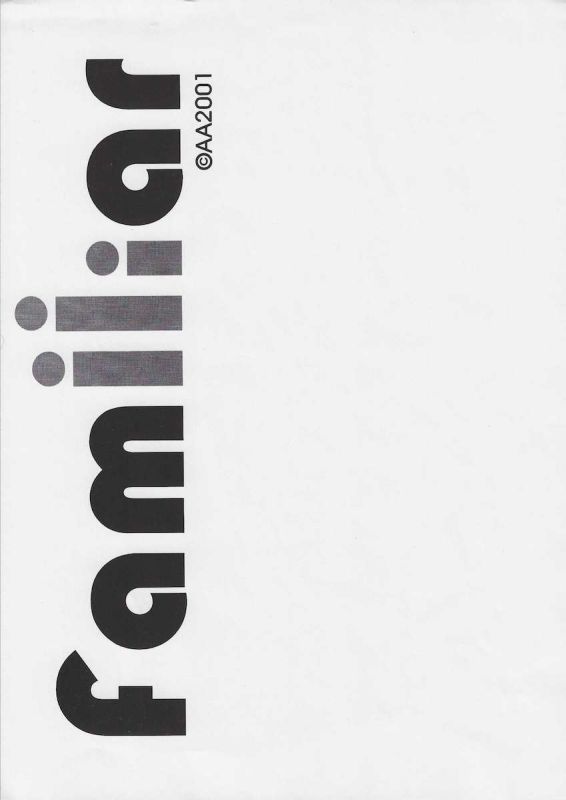
Familiar é uma impressão gráfica de Avelino de Araújo realizada em 2001, vinculada à poesia visual, à poesia experimental, à arte conceitual, à tipografia e às investigações intersígnicas relacionadas ao campo do Poema Processo.
Avelino de Araújo
Data: 2001
Dimensões: 29,5 x 21,1 cm
Familiar é uma impressão gráfica de Avelino de Araújo realizada em 2001, vinculada à poesia visual, à poesia experimental, à arte conceitual, à tipografia e às investigações intersígnicas relacionadas ao campo do Poema Processo. A composição utiliza a palavra familiar como estrutura central e transforma seus caracteres em elementos visuais autônomos. As letras aparecem em grandes dimensões, organizadas verticalmente na folha e impressas predominantemente em preto, enquanto as três letras i são apresentadas em tons de cinza. Os pontos e as hastes dessas letras possuem tamanhos diferentes, criando uma sequência semelhante a figuras humanas reunidas. Essa configuração permite interpretar os três caracteres como integrantes de uma família, possivelmente adultos e criança, estabelecendo uma relação direta entre a forma tipográfica e o significado da palavra. Avelino de Araújo converte a escrita em imagem e utiliza diferenças de escala, posição e tonalidade para construir uma representação sintética das relações familiares. As letras deixam de funcionar apenas como componentes linguísticos e passam a atuar como corpos, presenças e personagens. A palavra familiar também apresenta diferentes sentidos em português, podendo indicar aquilo que pertence à família, aquilo que é conhecido ou habitual e uma pessoa ligada por parentesco. A obra explora essa ambiguidade e aproxima reconhecimento verbal, identidade, convivência, semelhança e diferença. As três letras i destacadas sugerem indivíduos que compartilham a mesma estrutura básica, mas possuem proporções distintas, indicando diversidade dentro de uma unidade coletiva. O espaço vazio ao redor da palavra amplia sua presença e reforça a economia visual da composição. A orientação vertical exige que o observador modifique a posição habitual de leitura, transformando o ato de reconhecer a palavra em experiência corporal e perceptiva. Familiar integra a produção de Avelino de Araújo baseada na apropriação de letras, palavras e códigos tipográficos como matéria de construção poética e reflexão sobre relações humanas. Na proximidade da última letra aparecem a marca de autoria A A e o ano 2001. Palavras chave para indexação: Avelino de Araújo, Familiar, 2001, impressão gráfica, poesia visual brasileira, poema visual, poesia experimental, arte conceitual, Poema Processo, família, relações familiares, tipografia experimental, letras como figuras humanas, palavra imagem, texto imagem, escala tipográfica, identidade, parentesco, convivência, semiótica, intersigno, comunicação visual, arte gráfica brasileira, múltiplo gráfico, arquivo de poesia visual, arte brasileira do século vinte e um.TEXT FOR THE SALSA PROGRAM IN ENGLISH: Familiar is a graphic print by Avelino de Araújo produced in 2001 and associated with visual poetry, experimental poetry, conceptual art, typography and intersemiotic investigations related to the field of the Poema Processo movement. The composition uses the Portuguese word familiar as its central structure and transforms its characters into autonomous visual elements. The letters appear on a large scale, arranged vertically on the sheet and printed mainly in black, while the three letters i are presented in shades of gray. The dots and stems of these letters have different sizes, creating a sequence resembling a group of human figures. This configuration allows the three characters to be interpreted as members of a family, possibly adults and a child, establishing a direct relationship between typographic form and the meaning of the word. Avelino de Araújo converts writing into image and uses differences in scale, position and tone to construct a synthetic representation of family relationships. The letters no longer function only as linguistic components and begin to operate as bodies, presences and characters. In Portuguese, the word familiar may refer to something connected with the family, something known or habitual and a person related through kinship. The work explores this ambiguity and brings together verbal recognition, identity, coexistence, similarity and difference. The three highlighted letters i suggest individuals who share the same basic structure but possess different proportions, indicating diversity within a collective unit. The empty space surrounding the word strengthens its presence and reinforces the visual economy of the composition. The vertical orientation requires the viewer to alter the usual position of reading, transforming recognition of the word into a bodily and perceptual experience. Familiar belongs to Avelino de Araújo
s production based on the appropriation of letters, words and typographic codes as material for poetic construction and reflection on human relationships. The authorship mark A A and the year 2001 appear near the final letter. Keywords for indexing: Avelino de Araújo, Familiar, 2001, graphic print, Brazilian visual poetry, visual poem, experimental poetry, conceptual art, Poema Processo, family, family relationships, experimental typography, letters as human figures, word image, text image, typographic scale, identity, kinship, coexistence, semiotics, intersign, visual communication, Brazilian graphic art, graphic multiple, visual poetry archive, twenty first century Brazilian art.
Impressão gráfica em preto e tons de cinza sobre papel claro. A composição apresenta a palavra familiar em caracteres tipográficos de grandes dimensões, disposta verticalmente ao longo de uma das laterais da folha. As letras f, a, m, a, l e r aparecem em preto, com formas espessas, arredondadas e elevado contraste. As três letras i aparecem em cinza e possuem alturas diferentes. Seus pontos circulares também variam de tamanho e posição, reforçando a associação com três figuras humanas de diferentes proporções. A distribuição dos caracteres forma uma sequência contínua, mas cada letra mantém presença visual própria. A marca de autoria A A e o ano 2001 aparecem junto à parte superior da composição quando a palavra é observada em sua orientação de leitura. O restante da folha permanece praticamente vazio, criando forte contraste entre a área impressa e o campo branco. O suporte apresenta leves ondulações, marcas de dobra, vincos e sinais de manuseio, especialmente nas margens e na região superior. A peça pode ser classificada como poema visual, impressão de artista, múltiplo gráfico, estudo tipográfico e documento conceitual, sendo relevante para pesquisas sobre Avelino de Araújo, Poema Processo, poesia visual, família, identidade, tipografia, semiótica, linguagem e produção gráfica brasileira.OBSERVATION TEXT IN ENGLISH: Graphic print in black and shades of gray on light colored paper. The composition presents the Portuguese word familiar in large typographic characters arranged vertically along one side of the sheet. The letters f, a, m, a, l and r appear in black with thick rounded forms and strong contrast. The three letters i appear in gray and have different heights. Their circular dots also vary in size and position, strengthening the association with three human figures of different proportions. The arrangement of the characters forms a continuous sequence, although each letter maintains an independent visual presence. The authorship mark A A and the year 2001 appear near the upper section when the word is viewed in its reading orientation. The rest of the sheet remains almost entirely empty, creating strong contrast between the printed area and the white field. The support shows slight undulations, fold marks, creases and traces of handling, especially along the margins and upper region. The piece may be classified as a visual poem, artist print, graphic multiple, typographic study and conceptual document, making it relevant to research on Avelino de Araújo, Poema Processo, visual poetry, family, identity, typography, semiotics, language and Brazilian graphic production.
Familiar is a graphic print by Avelino de Araújo produced in 2001 and associated with visual poetry, experimental poetry, conceptual art, typography and intersemiotic investigations related to the field of the Poema Processo movement.